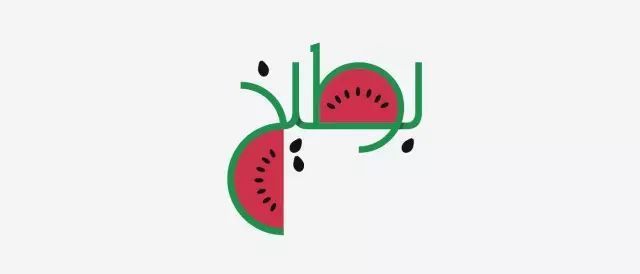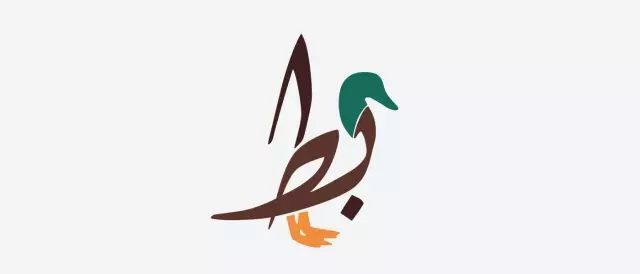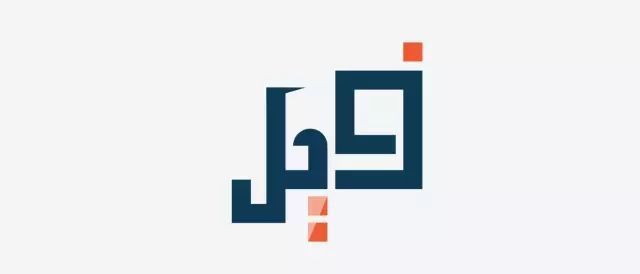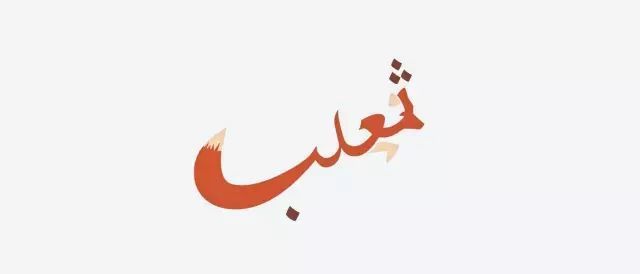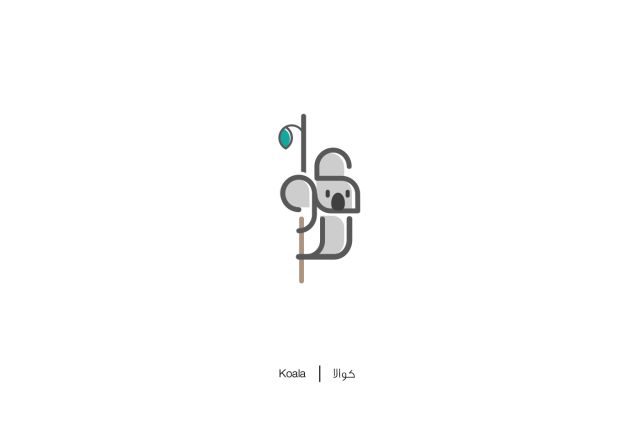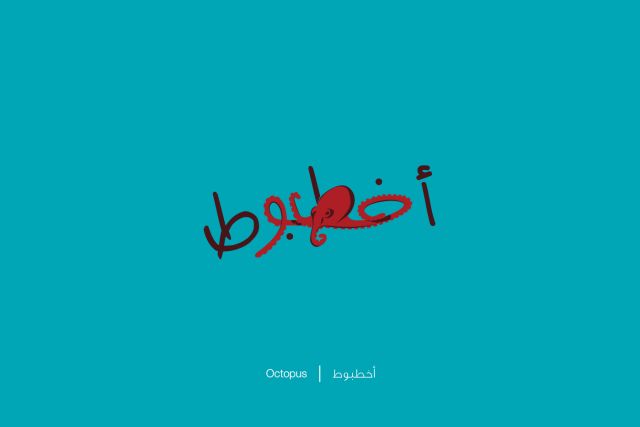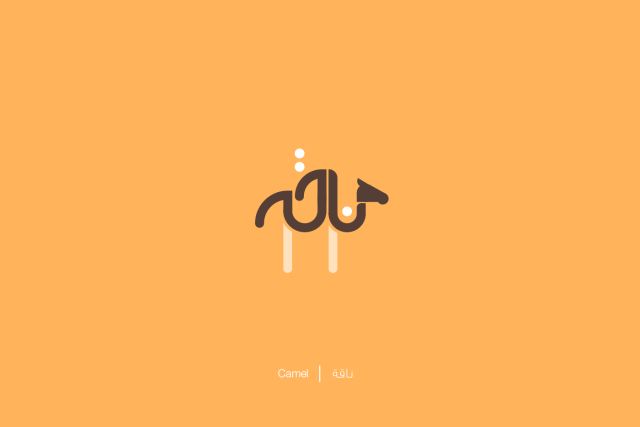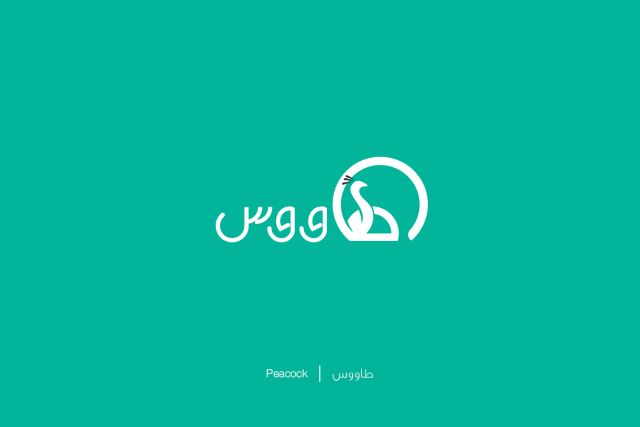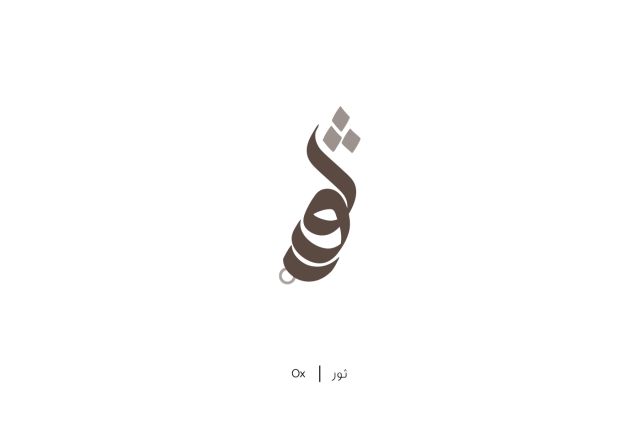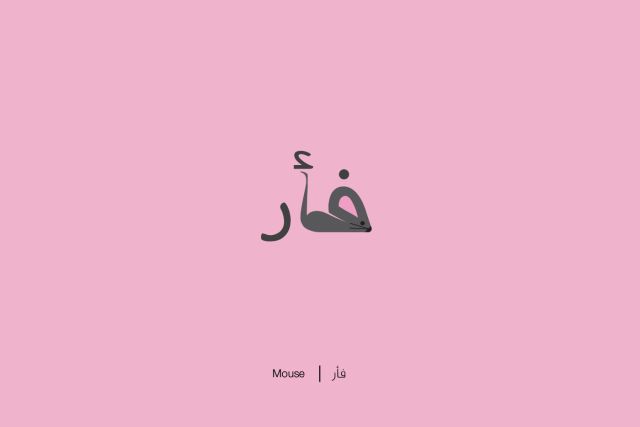
阿拉伯的字体设计师作品看过没?
我们常说,什么样的设计才是好的设计?就是短时间内让人明白所表达的诉求。设计领域很多,大部分的商业设计,都会有类似这样的要求。今天看到一个字体设计案例,就很好的诠释了什么叫做秒懂。
首先,下面这些字体都是阿拉伯语中的文字,由埃及设计师 Mahmoud Tammam 设计。这套字体设计的厉害之处就在于,完全不懂阿拉伯语的我们,也能一眼看懂这个单词表达的是啥。
比如下面这个تاج在英文里是 crown 的意思,也就是皇冠。
بطيخ 对应的英文单词是watermelon,是不是很形象?
这个不用说了,是猫的意思。
这个我没有去查,但肯定是鸟,或者其他细分的某种鸟类的单词。
这个,各位觉得是什么?
答案:فيل elephant 大象
这个是狗
这个是熊
这个是狐狸
这个单词我还特意去查了一下,是 حبر ink 墨水
这个是城堡的意思,原文应该是这样:قلعة是不是很形象?
这个是羚羊
长颈鹿
狮子:
这个是Tea 原单词是这样的:شاي
这个造型特别有趣,对应的单词是whale,也就是鲸鱼,原单词是这样的حوت,真的很像一条鱼
下面几个我都放出阿拉伯语的原单词,对比着设计的造型,看看能认出表达的意思吗?
حرية
هي
قرد
还有一部分作品作者直接标注了原单词和对应的英文单词,让非阿拉伯语的人可以更好的理解他的设计。
别的语言的字体设计方式,恰恰是最有利于帮助我们提升设计感的,因为能只吸取创意和手法本身,必须再将其融会贯通用在汉字设计上,算是真正的提升了设计创意的本领。